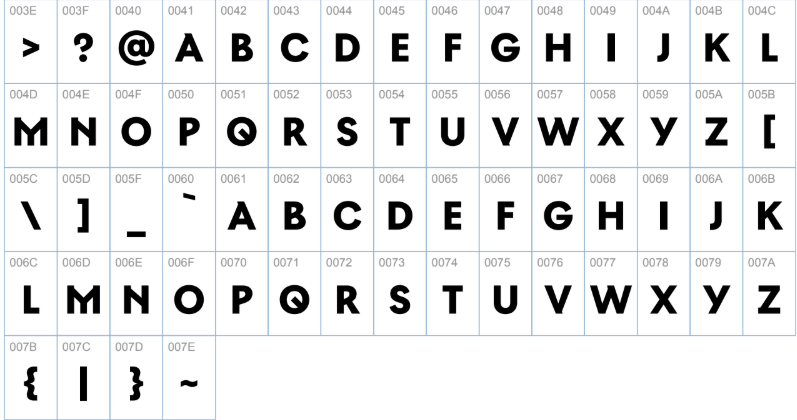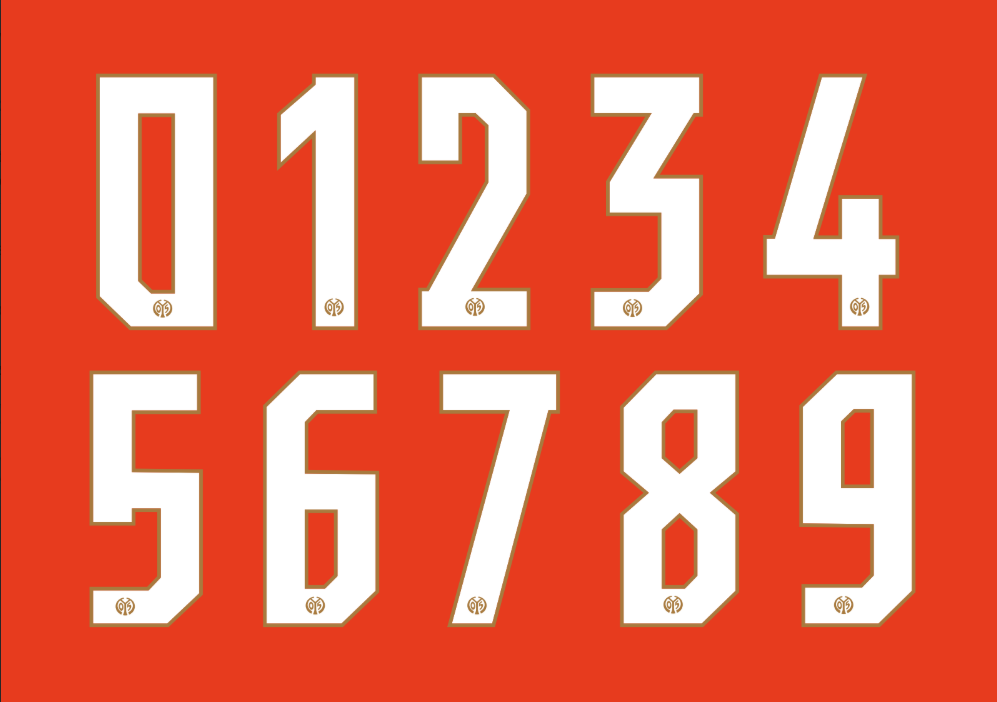
A Bundesliga é conhecida por seus designs vibrantes e tipografias modernas, e o Mainz 05 não fica para trás. Para a temporada 2025/2026, a fornecedora Jako manteve o padrão de qualidade, entregando uniformes que celebram a identidade do clube da Renânia-Palatinado.
- Conteúdo: Numeração completa e alfabeto em caixa alta (uppercase), incluindo caracteres especiais alemães (umlaut).
Estilo Visual e Aplicação
A tipografia do Mainz 05 assinada pela Jako apresenta um visual limpo e contemporâneo. Com traços de espessura média e cantos levemente suavizados, a fonte oferece excelente legibilidade tanto no estádio quanto na TV.
O design evita excessos decorativos, focando na funcionalidade e na harmonia com o patrocínio e o escudo do clube. É uma fonte versátil que funciona muito bem sobre o vermelho intenso da camisa titular, transmitindo a organização e a energia características do futebol alemão.